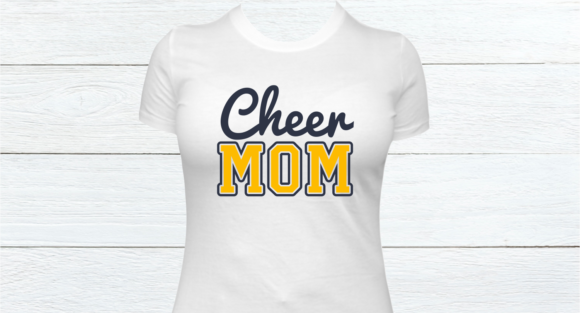
JP Sport Jersey Font
JP Sport Jersey Font – الخط المثالي للتصاميم الرياضية والاحترافية! ????⚡
JP Sport Jersey Font هو خط عصري وقوي مستوحى من الأرقام والحروف المستخدمة في قمصان الفرق الرياضية. يتميز بتصميم حاد وزوايا دقيقة تمنحه مظهرًا احترافيًا وجريئًا، مما يجعله خيارًا مثاليًا للمشاريع التي تحتاج إلى طابع ديناميكي وقوي.
???? المميزات:
✔ تصميم هندسي حاد يعكس الطابع الرياضي
✔ مثالي لقمصان الفرق، الشعارات، الملصقات، والتصاميم الدعائية
✔ وضوح عالي وأسلوب قوي يعزز هوية العلامة التجارية
✔ يدعم أنماطًا متعددة لاستخدامات متنوعة
ارفع مستوى تصاميمك الرياضية وأضف لمسة احترافية مع JP Sport Jersey Font! ????????